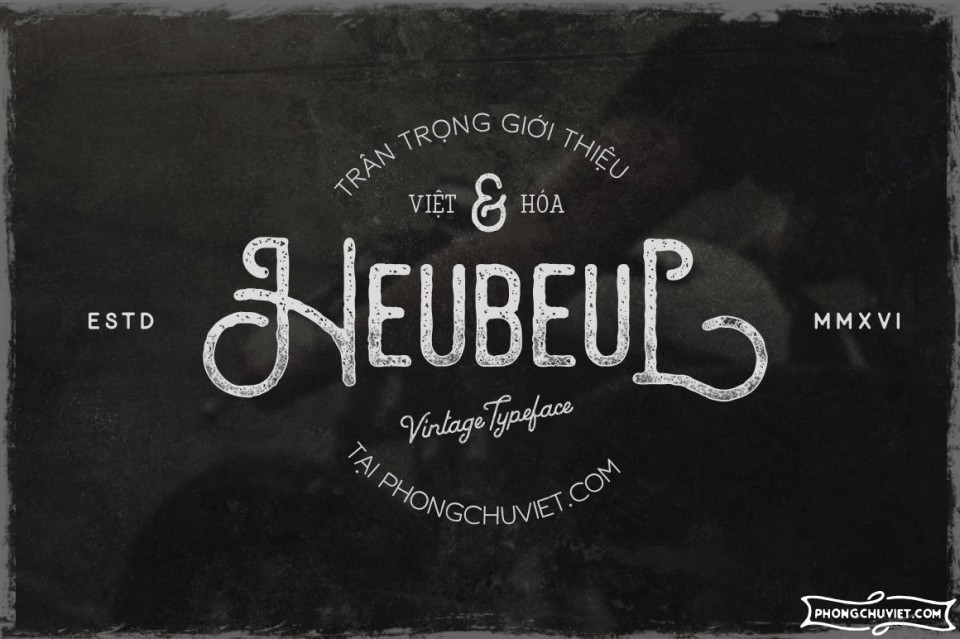
Tải Font việt hóa FS Heubeul kiểu Vintage cực đẹp cho thiết kế hoài cổ
Giới thiệu về bộ Font việt hóa FS Heubeul kiểu Vintage
Trong thế giới đồ họa hiện đại, việc tìm kiếm một bộ Font Miễn Phí có phong cách cổ điển luôn là ưu tiên hàng đầu của các nhà thiết kế. Font việt hóa FS Heubeul kiểu Vintage là một lựa chọn hoàn hảo nhờ sự kết hợp tinh tế giữa nét chữ thô mộc và tinh thần Retro đặc trưng. Bộ font này được đội ngũ chuyên môn chỉnh sửa kỹ lưỡng nhằm hỗ trợ đầy đủ bảng mã tiếng Việt, giúp bạn dễ dàng sử dụng trong các phần mềm như Photoshop, Illustrator hay Canva mà không lo lỗi hiển thị dấu câu.
Đặc điểm nổi bật của FS Heubeul
FS Heubeul gây ấn tượng mạnh bởi những đường nét không hoàn hảo một cách cố ý, tạo cảm giác như được vẽ bằng tay trên nền giấy cũ. Đây là font chữ thuộc phong cách Serif với chân chữ dày, mang lại sự vững chãi nhưng vẫn đầy tính nghệ thuật. Font chữ này rất phù hợp cho các dự án thiết kế logo, bìa sách, thực đơn quán cà phê hoặc các ấn phẩm truyền thông mang hơi hướng thập niên 80-90. Sự linh hoạt của nó cho phép người dùng biến hóa đa dạng từ phong cách bụi bặm đến thanh lịch.
Cách ứng dụng Font việt hóa FS Heubeul kiểu Vintage hiệu quả
Để tối ưu hóa vẻ đẹp của Font việt hóa FS Heubeul kiểu Vintage, bạn nên kết hợp với các tông màu trầm như nâu đất, vàng nghệ hoặc xanh rêu. Việc sử dụng các hiệu ứng texture như vết xước hay bụi giấy sẽ càng làm tôn lên chất cổ điển của bộ font. Ngoài ra, hãy chú ý đến khoảng cách giữa các chữ cái (kerning) để đảm bảo văn bản luôn dễ đọc và chuyên nghiệp nhất trong mắt người xem.